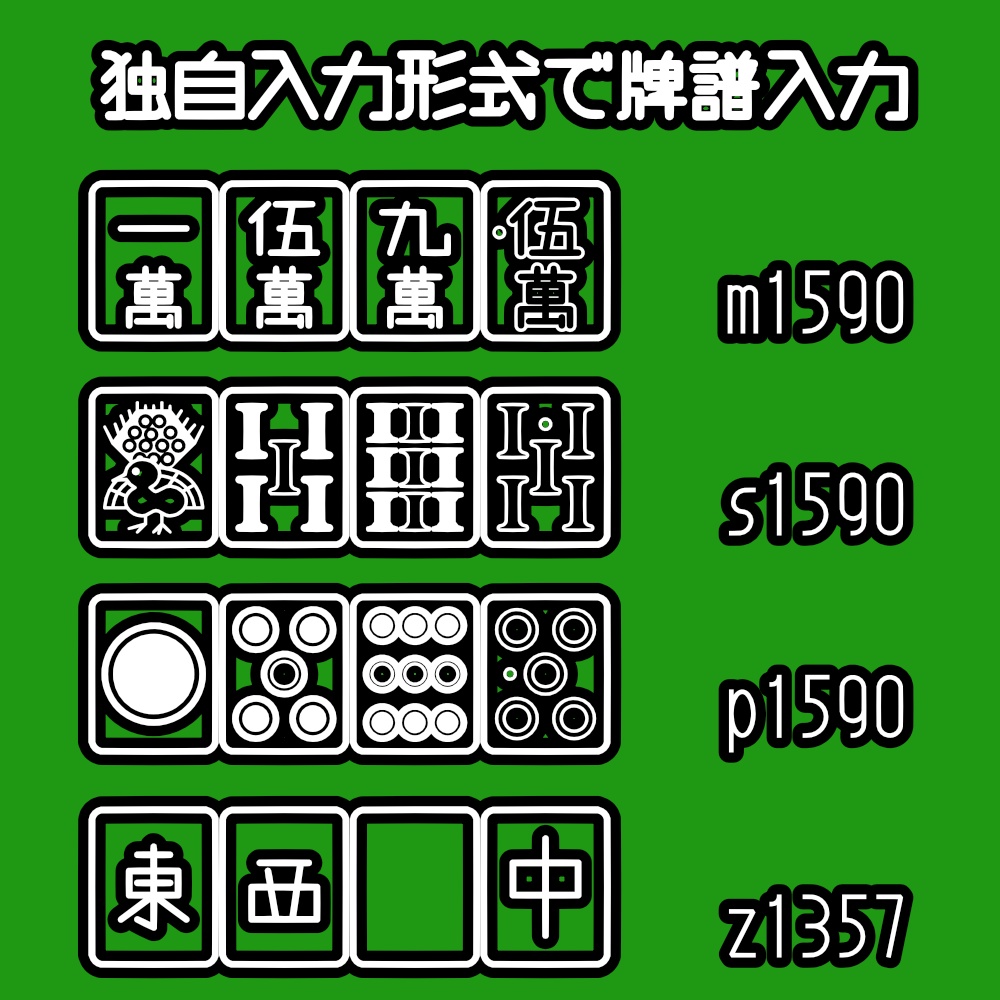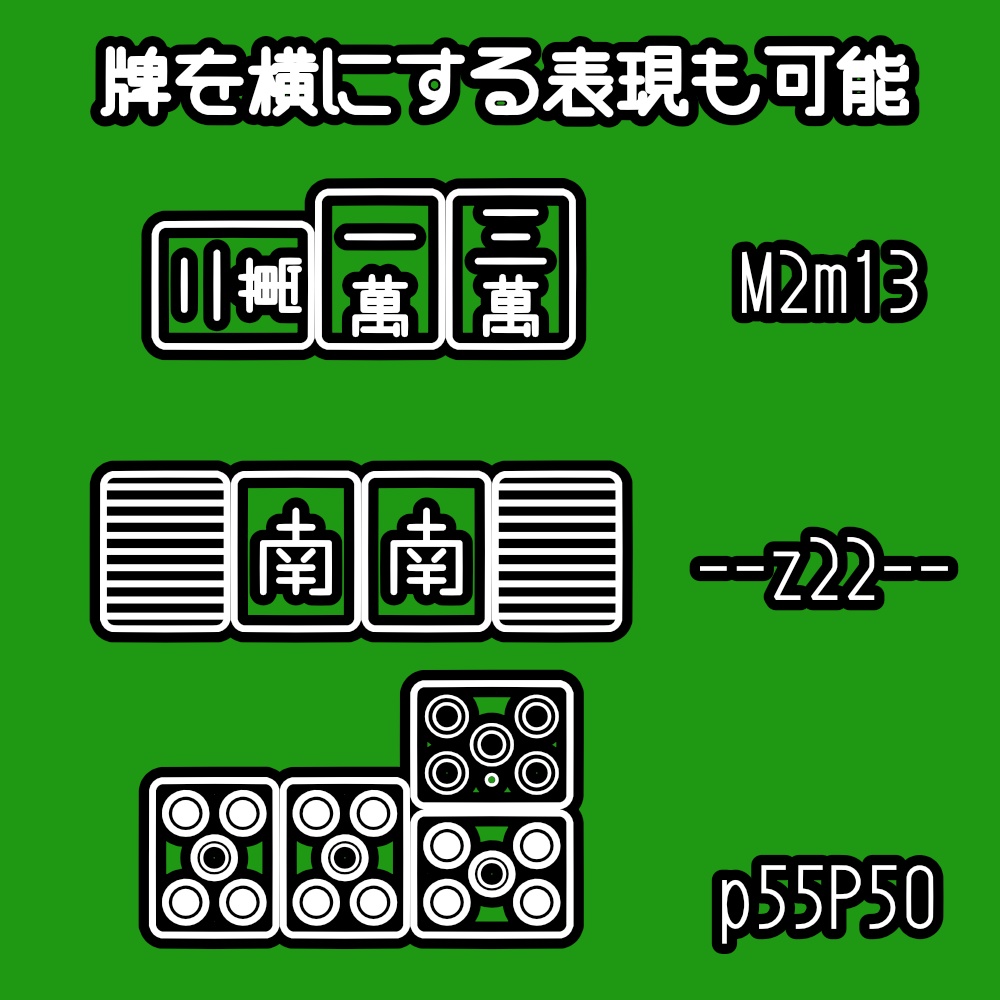
フォント MahjongZSPM
麻雀牌のフォントです。 タイポグラフィ(OpenType機能)の欧文合字(liga)と文脈依存の異体字(calt)を使用する事で 従来の文字割り当てに比べて直感的な入力が可能となっており、作業効率が大幅に向上します。
牌種記号[m,p,s,z]と牌番号[0-9]を入力すると、その内容に応じた麻雀牌が表示されます。 m0-m9:萬子 0は赤5 s0-s9:索子 0は赤5 p0-p9:筒子 0は赤5 z1-z7:東南西北白發中 数字を続けて入力すると、前文字の牌種を引き継ぎます。 m1235:1萬2萬3萬5萬 z1127:東東南中 大文字の牌種記号(M,P,S,Z)と牌番号(0-9)を入力すると、牌を横に表示します。 大文字の牌種記号(M,P,S,Z)と牌番号(0-9)を2回入力すると、牌を横に表示し重ねます(ゾロ目、05、50のみ有効)。 --と入力すると、牌を裏側にして表示します。 これらは数字を続けて入力しても、前文字の牌種を引き継ぎません。 都合により、MPSZ形式から牌番号(0-9)と牌種記号(m,p,s,z)が逆転しています。 例:九連宝燈九面待ち MPSZ形式 : 1112345678999m 本フォント形式 : m1112345678999 横に2段重ねた文字はアセントより上に突き出します。 アセントより突き出るものを作画しないソフトウェアでは正しく表示されない場合があります。 例) OBS 30.2.2 の ソース[テキスト(GDI+)](1行目を空行にして空きを作ると表示されます) UNICODEには麻雀記号の割り当て(1F000~1F02F)がありますが、本フォントでは使用していません。